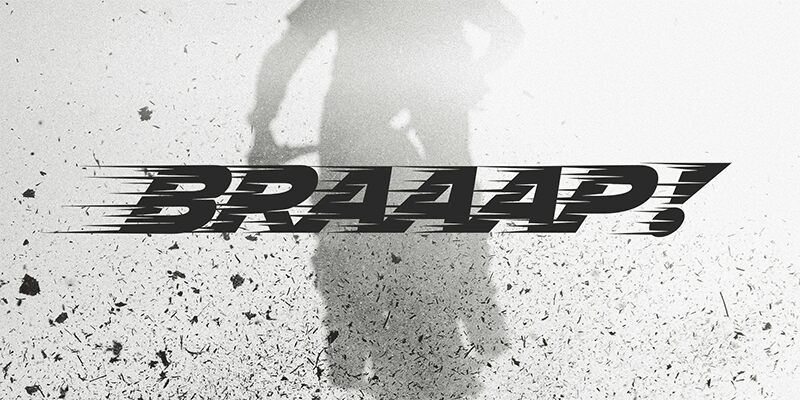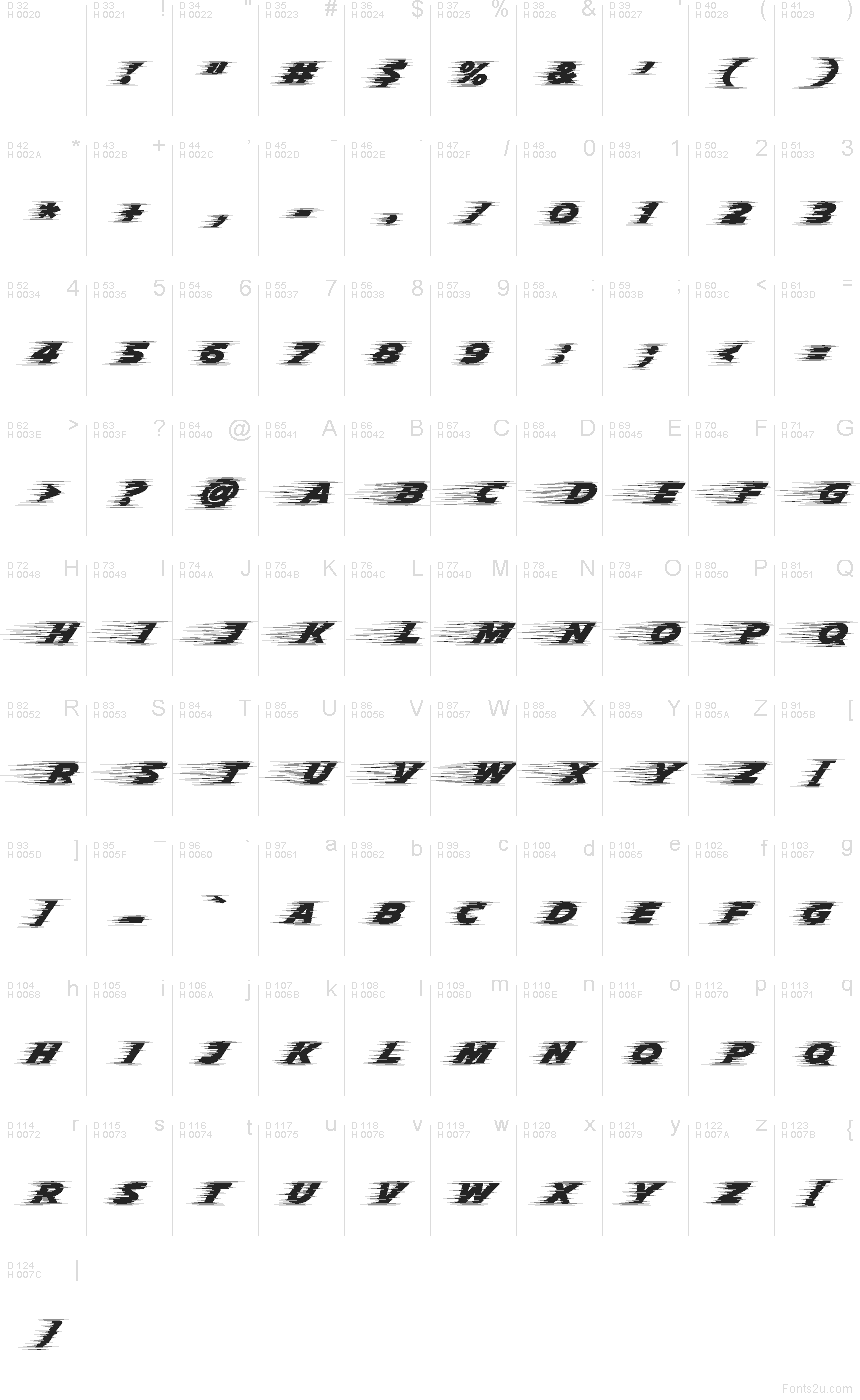
Braaap-S4 od Youssef Habchi je bezplatné písmo typu display se zkosenými blokovými tvary, které protínají rychlé horizontální pruhy a zubaté zlomy. Opakující se efekt řezu dodává písmenům svižný rytmus inspirovaný závoděním, aniž by přitom ztratila svou silnou a kompaktní siluetu.
Braaap-S4 skvěle funguje na plakátech motoristických sportů, v názvech her, na letácích k akcím, ve sportovním brandingu a v grafických nadpisech, které potřebují vyjádřit pohyb. Toto bezplatné písmo se také hodí pro logotypy, akční bannery a krátké propagační texty, kde roztříštěné pruhy přenášejí energii rychlosti a údernosti.